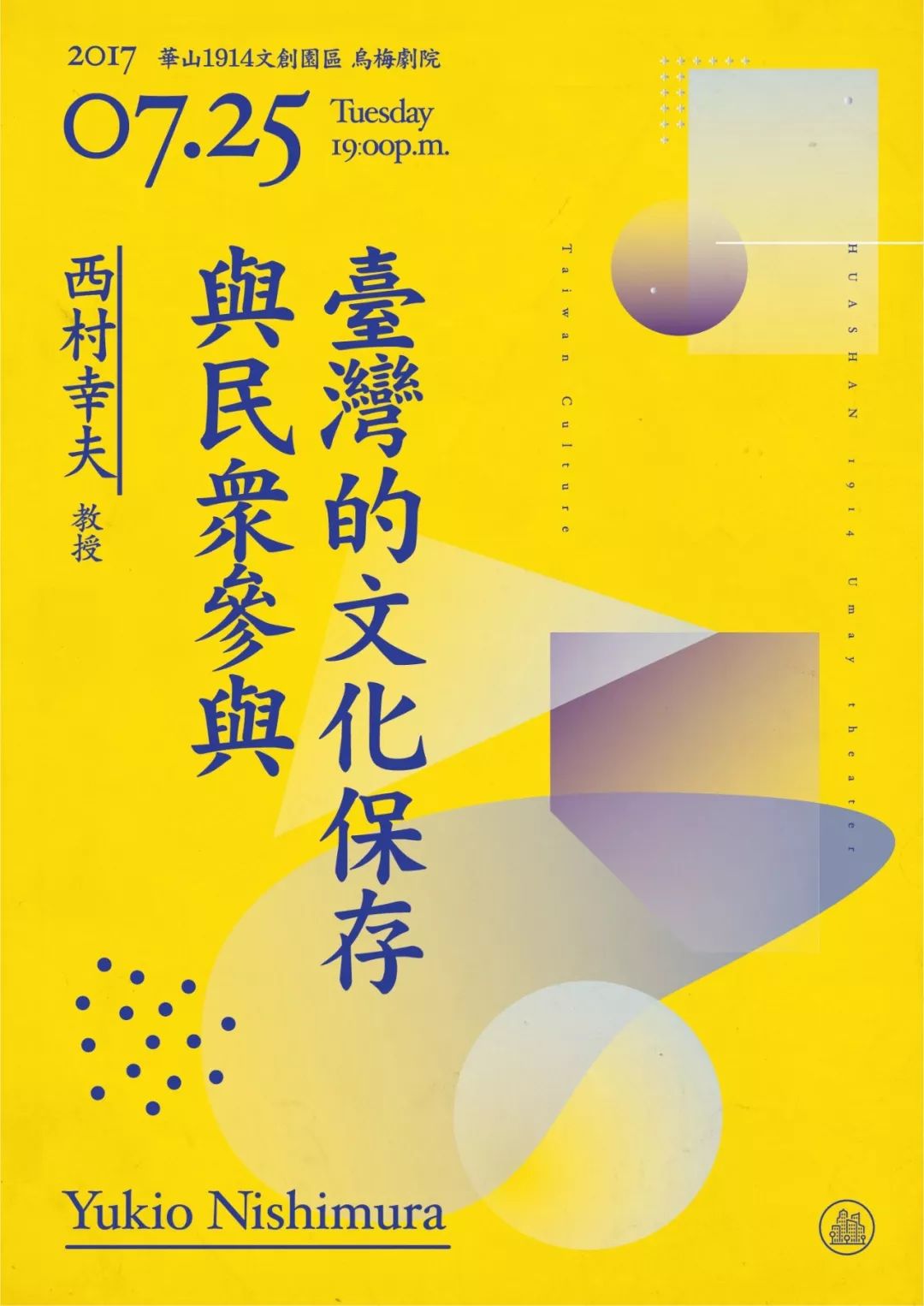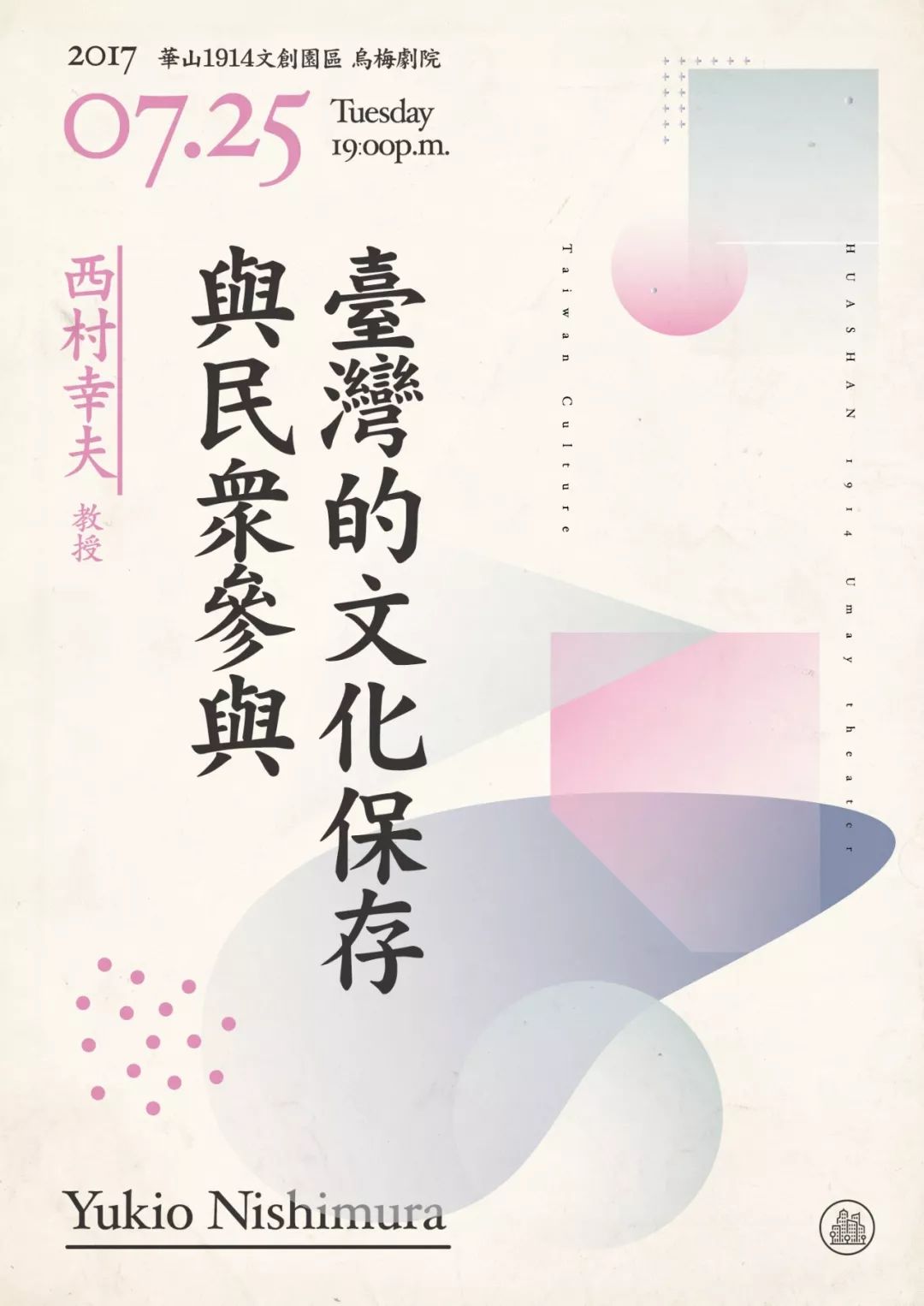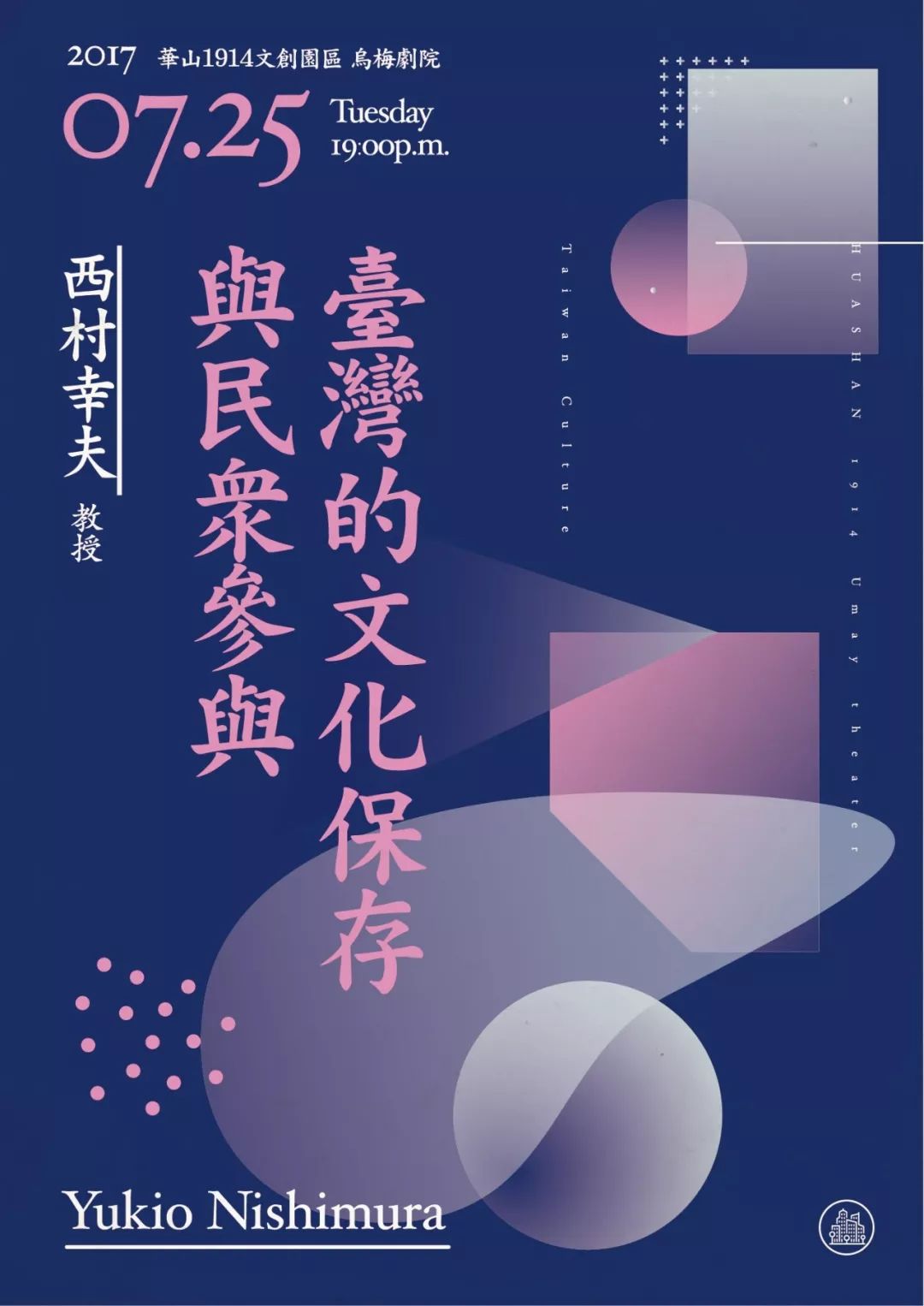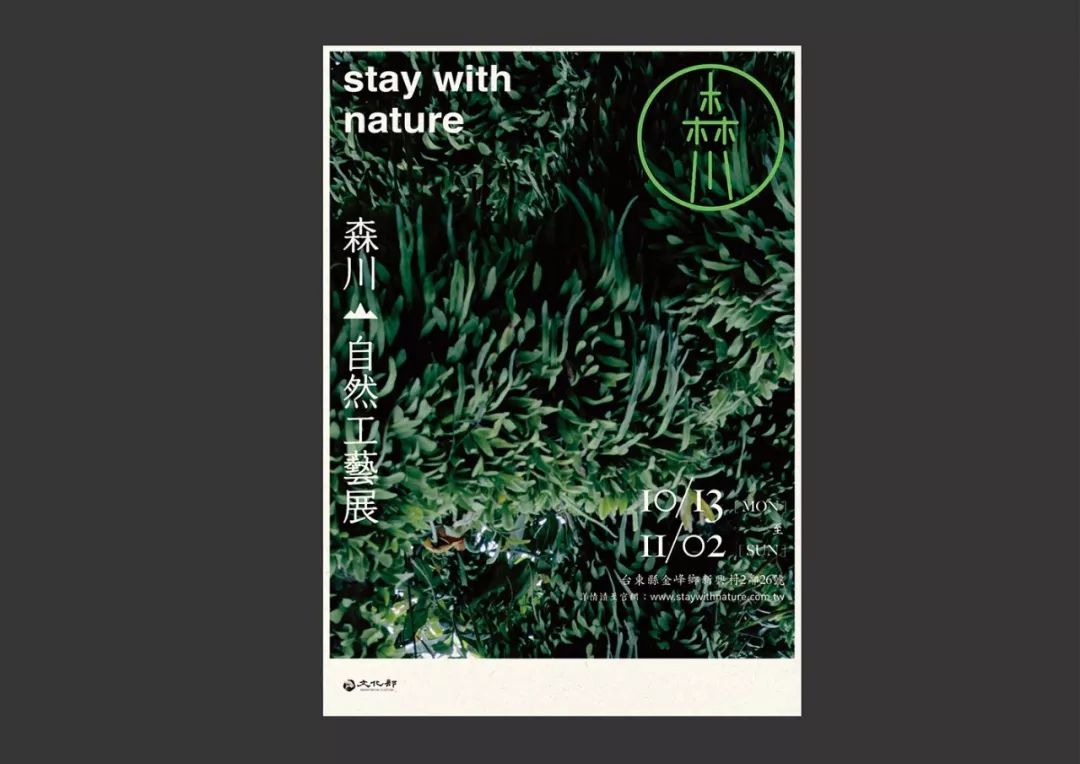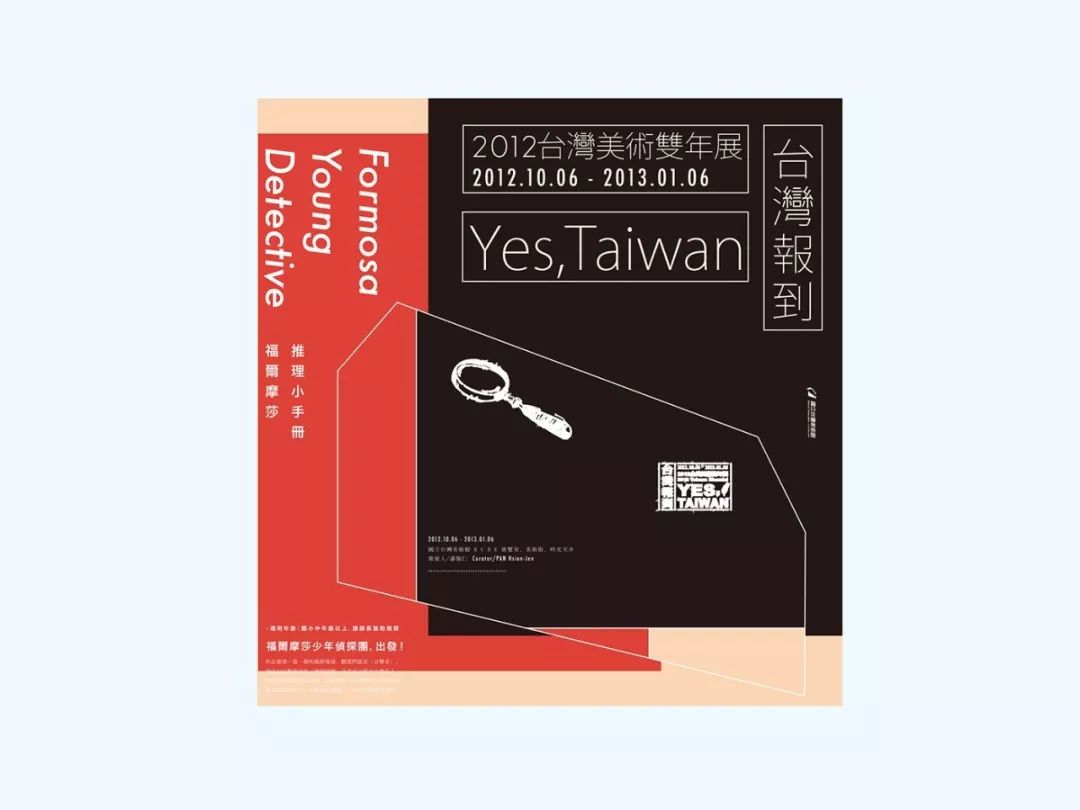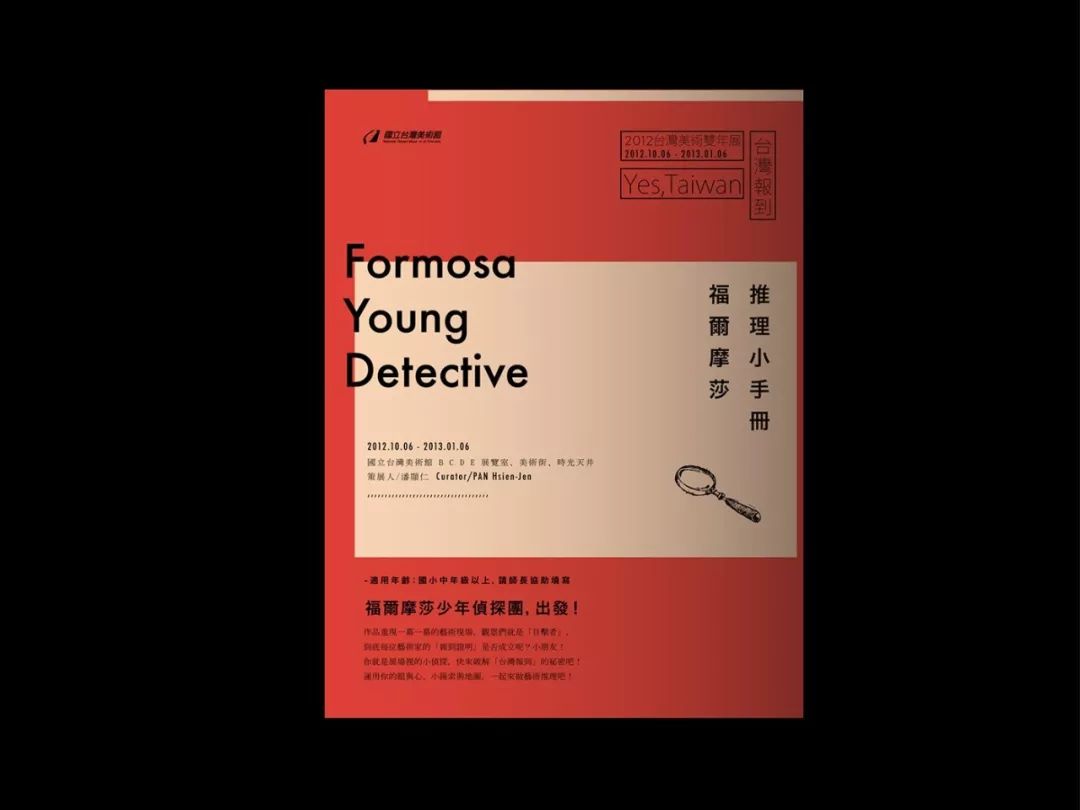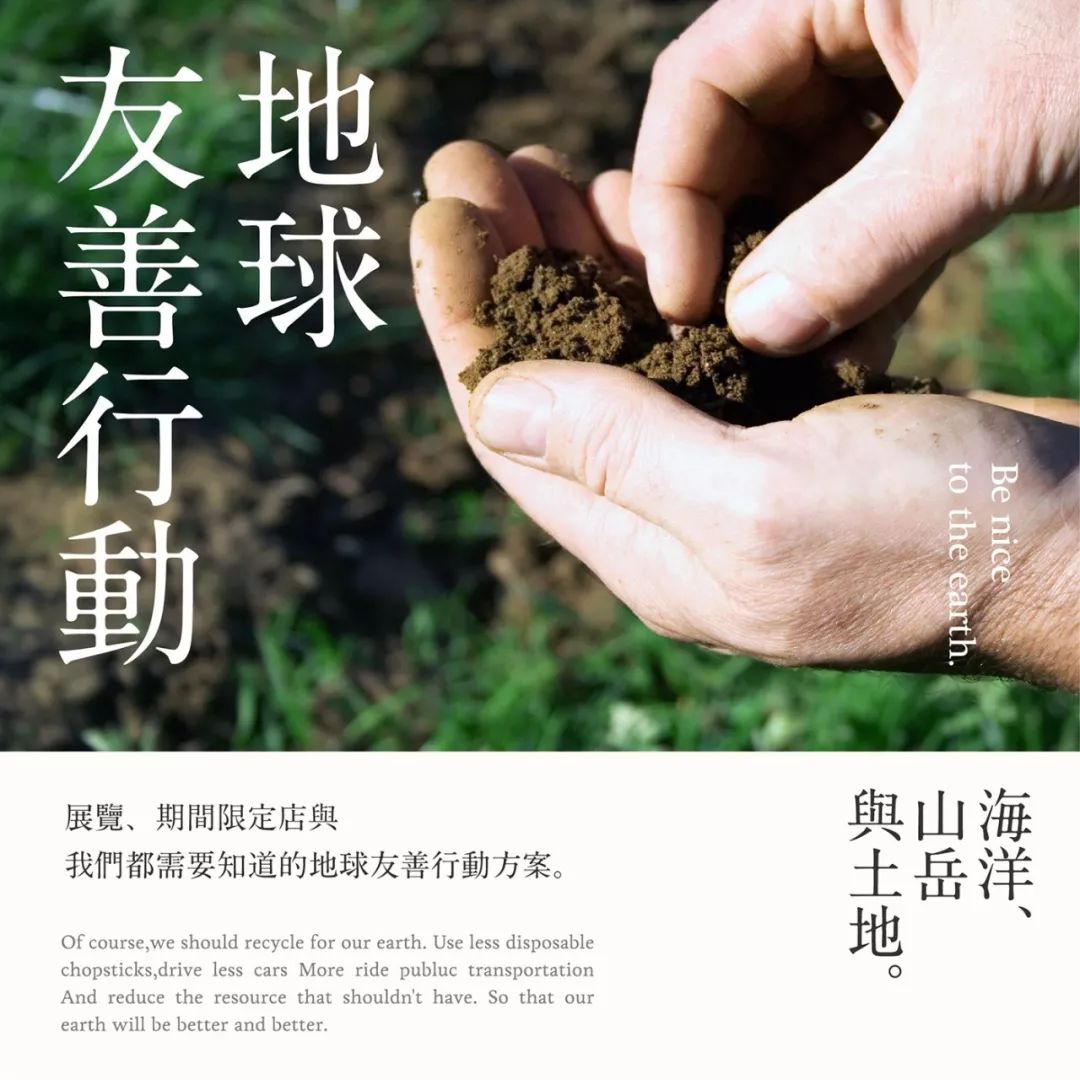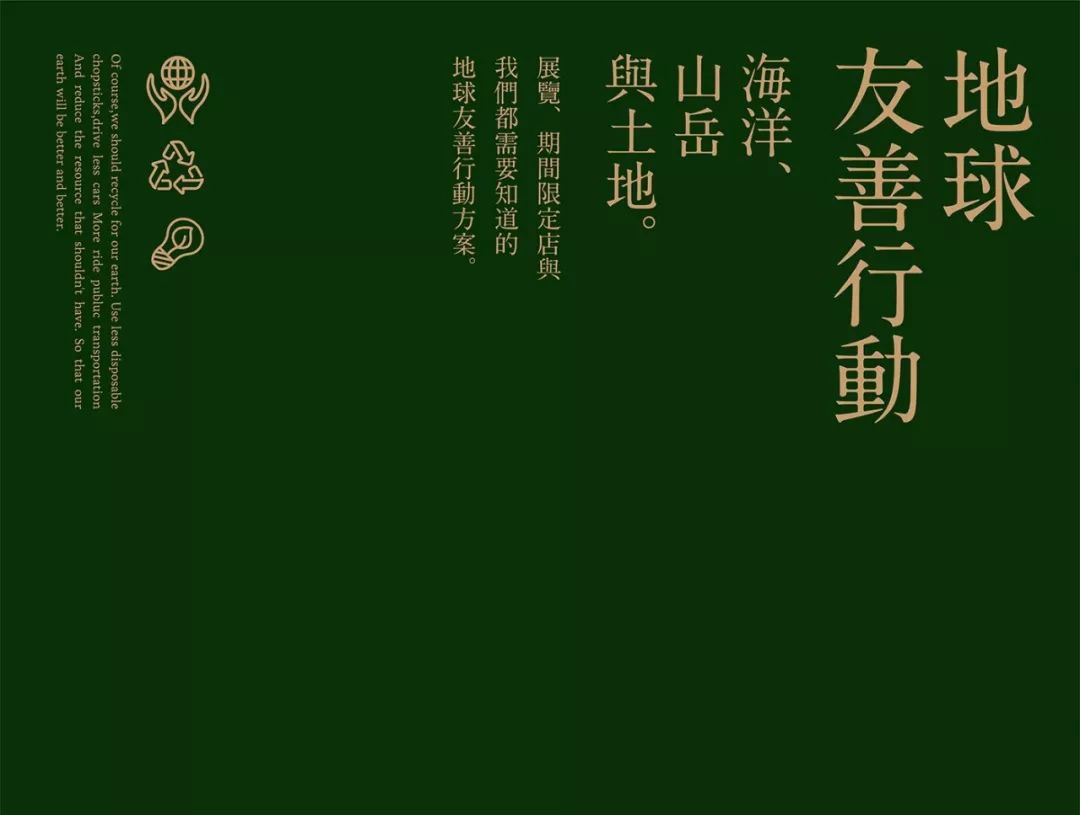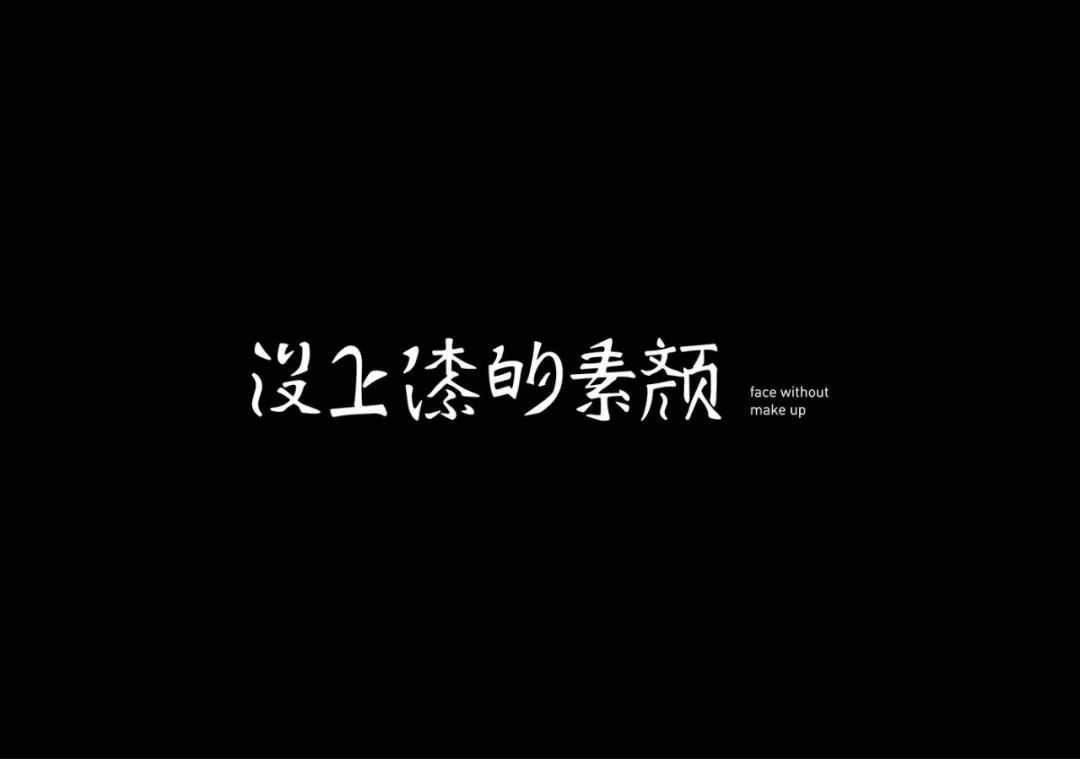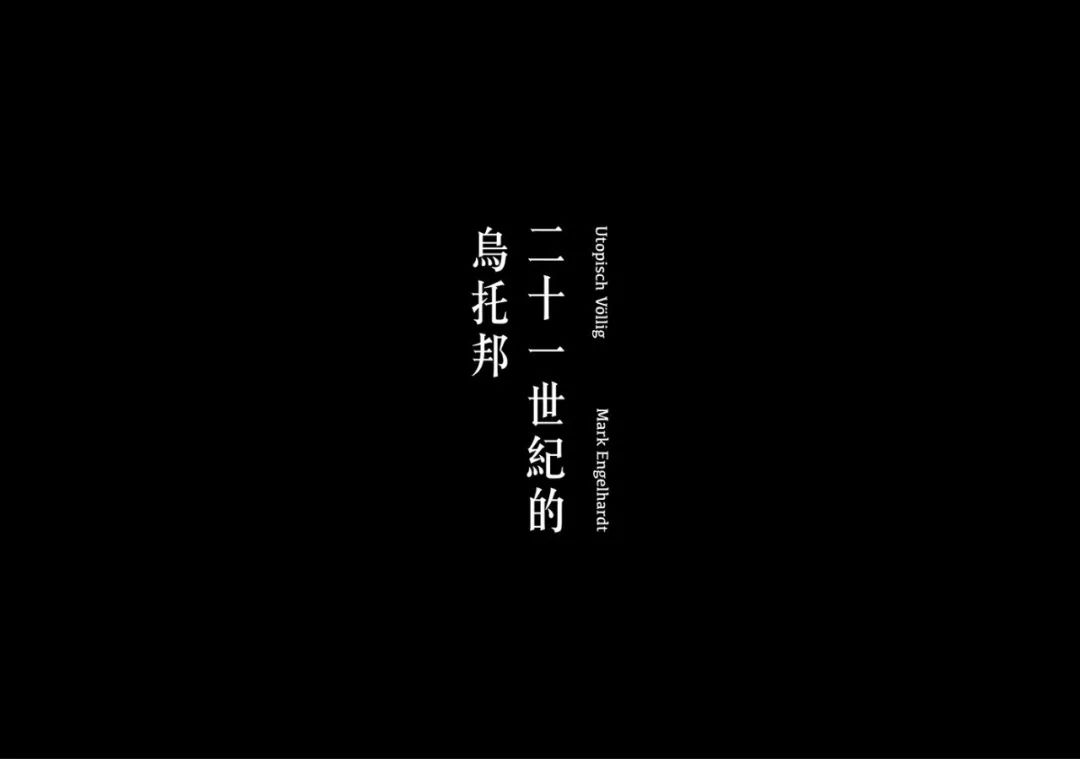
台北设计师 Lin Chen 海报字体作品分享,排版功力深厚!
在整个平面海报中,文字与图案是一种水乳交融的关系,是互为补充的关系,是相辅相承的关系。文字排列组合的好坏,直接影响版面的视觉传达效果。
今天,和大家分享来自台北设计师 Lin Chen 平面海报作品,大家不妨看看其文字排列与组合,包括字体风格、大小、方向、明暗度等方面。希望能给大家带来灵感。
Exhitbition ● Robert Capa 在现场百年回顾展
文字的主要功能是向阅读者传达作者的想法和各种信息,要达到这一目的,必须给人以清新的视觉印象。
Poster ● SORI YANAGI 柳宗悦 / 柳宗理 思想作品对话展
Poster ● HETERO-TOPIA 异托邦 百年城市史下的文化閒逛
Poster ● Yukio Nishimura 东京大学:西村幸夫教授讲座
Branding|Wood Brand : 森川
Exhibition|Yes Taiwan ! Taiwan Biennial 台湾美术双年展
Festival|CoDance Festival 相遇舞蹈节
最后,来一组Logo Collection . 字体设计
平面海报中设计,不同的字体具有不同的视角感受。文字排列组合的好坏,直接影响版面的视觉传达效果。因此,文字设计是增强视觉传达效果,提高作品诉求的有力武器。